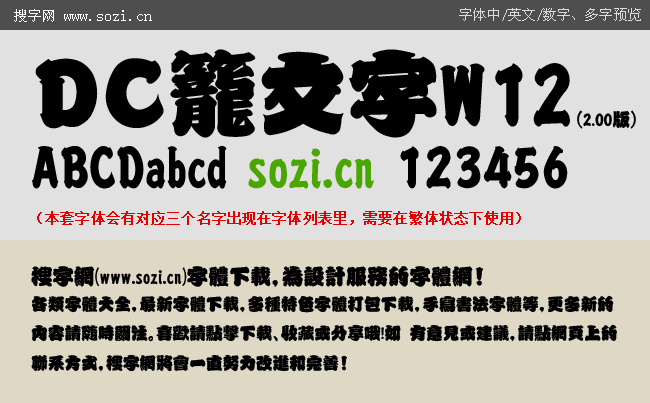
DC籠文字W12
搜字網(wǎng)提供一款DC籠文字W12日本中文藝術(shù)字體下載,DC籠文字W12是一款非常厚實(shí)的藝術(shù)字體,該字體端正醒目,粗壯有力,可用于標(biāo)題設(shè)計(jì),也適用于平面廣告,海報(bào)設(shè)計(jì)等廣告設(shè)計(jì)場(chǎng)合使用。